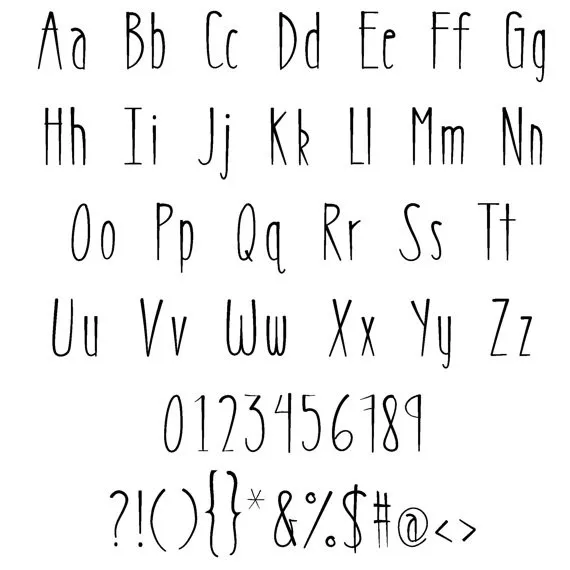
MRF Pixeldust Font – Download Grátis
A fonte “MRF Pixeldust Font” é uma escolha perfeita para adicionar um toque único e retro a qualquer projeto visual, especialmente quando se trata de criar interfaces de jogos ou designs infantis. Desenvolvida pela designer Sabrina Schleiger, esta fonte retrata uma estética nostálgica do início dos anos 2000, com seus pixels artificiais vibrando em cores vitoriosas. Ela é perfeita para aqueles que buscam dar um toque atraente e moderno às imagens digitais sem perder o charme retro característico do estilo pixellado. Com seu design elegante mas ainda assim divertido, “MRF Pixeldust Font” se destaca em qualquer projeto. É ideal para adicionar um elemento de nostalgia ou criatividade ao seu próximo design gráfico ou art visual, seja ele uma simples ilustração ou algo mais complexo como uma interface de jogo vintage. Seja qual seja o seu objetivo de design, esta fonte certamente não apenas reforça sua identidade visual, mas também adiciona um toque especial e memorável ao seu trabalho final.
Designer: Sabrina Schleiger